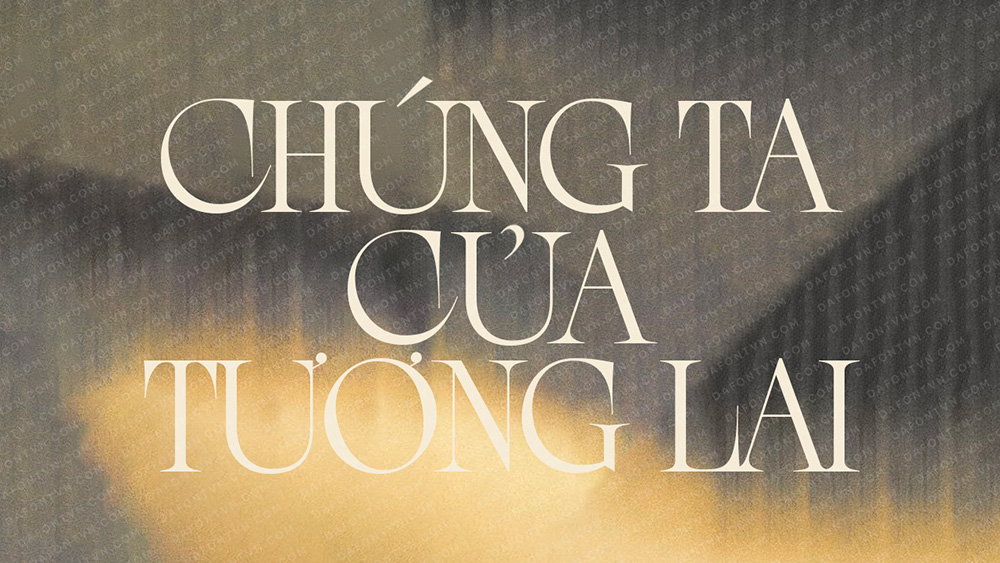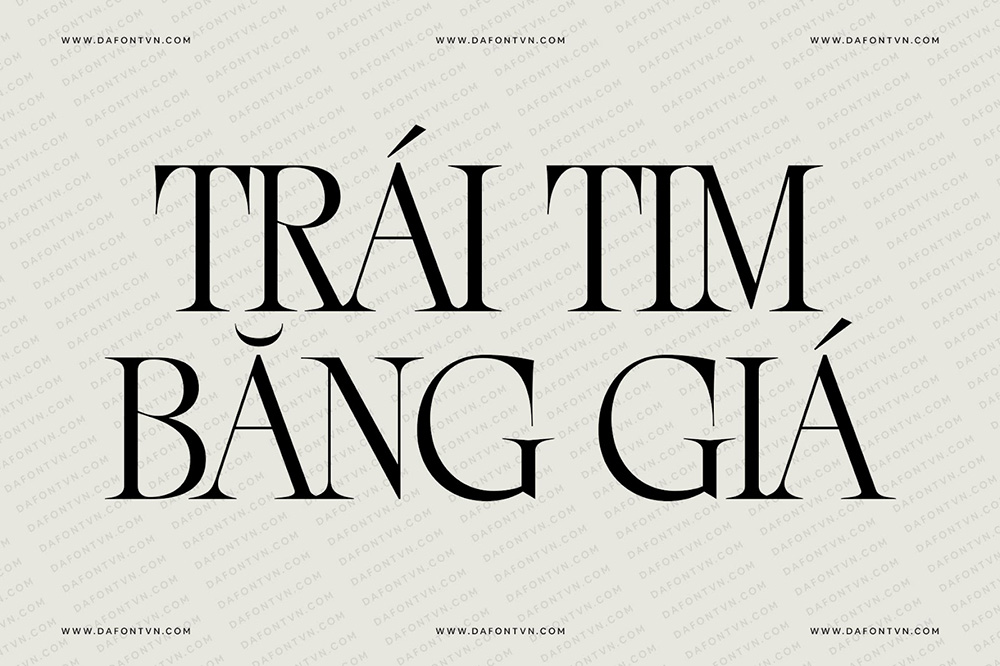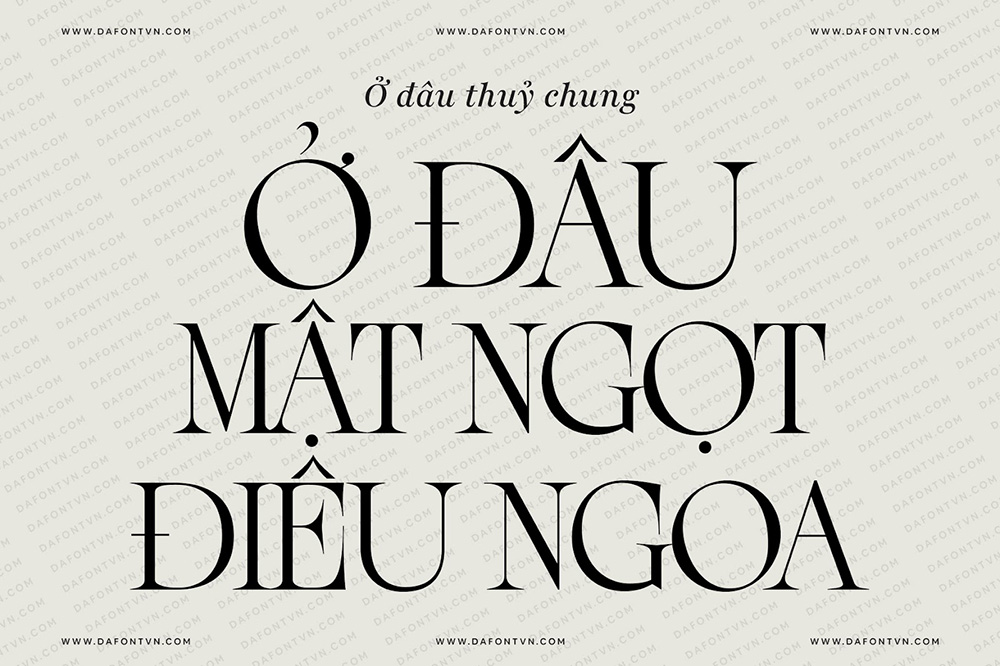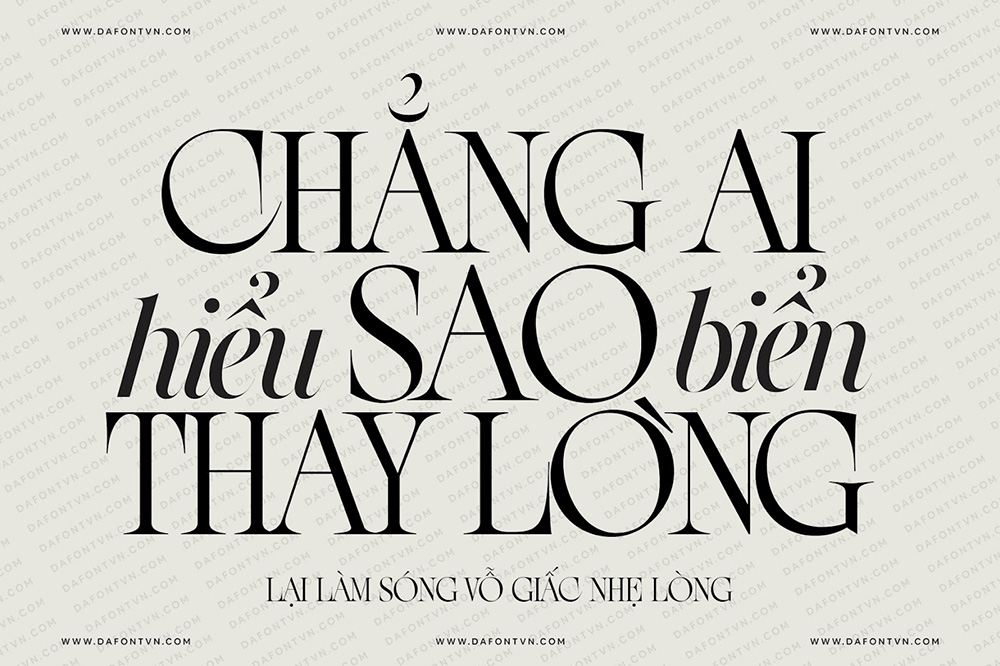
Font Việt Hóa - New Eddy Font MV Chúng Ta Của Tương Lai
Tối 22/2, Sơn Tùng bất ngờ tung poster chính thức giới thiệu MV Chúng Ta Của Tương Lai, MV sẽ ra mắt vào ngày 8/3/2024. Chắc chắn anh em sẽ chú ý đến là font chữ "Chúng ta của tương lai" của poster này.
Đây là font New Eddy, một font chữ hiển thị siu đẹp, nó được tạo ra cho một nhiệm vụ rất cụ thể: xuấn hiện trên màn hình khổng lồ trong buổi biểu diễn khiêu vũ. Mục đích là để đẩy lùi các giới hạn về độ tương phản trong khi vẫn có thể đọc được về mặt kỹ thuật trên quy mô lớn. Kết quả là kiểu chữ tiêu đề được ra mắt với độ dày đều đặn, được đánh dấu bằng độ tương phản rõ rệt và các serif phóng đại mang lại cho nó một các tính độc đáo.
New Eddy nổi bật với những đường nét dài, thon gọn và phần đầu chữ cao, cố tính được tạo ra nét biếm họa nhưng vẫn dễ đọc và ổn định. Điểm khác biệt là nhịp điệu ở từng chữ cái của nó, là kết quả của sự kết hợp giữa các hình tròn đặc biệt lớn và các chữ cái hẹp hơn. Điều này tạo ra một kết cấu typographic hấp dẫn khi được sử dụng để soạn từ và văn bản.
Một số kiểu chữ của New Eddy thậm chí còn có cấu trúc gợi nhớ đến các kiểu chữ theo phong cách Art Deco, nó thể hiện rất nhiều cá tính thông qua hình dạng của nó, khiến nó trở thành một kiểu chữ hiện đại đầy nổi bật, rất thích hợp sử dụng làm tiêu đề khi sử dụng ở kích thước lớn.
Font Việt Hóa - New Eddy Font MV Chúng Ta Của Tương Lai